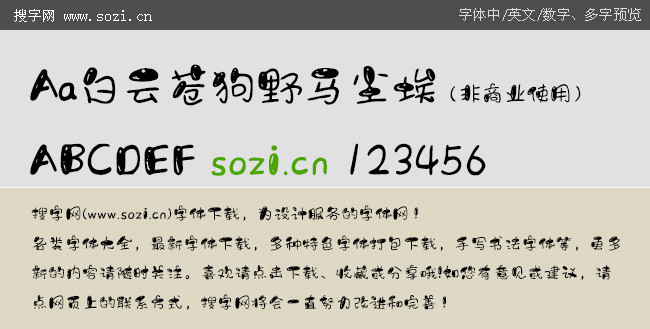
Aa白云蒼狗野馬塵埃
搜字網(wǎng)給大家提供一款A(yù)a白云蒼狗野馬塵埃(非商業(yè)使用)中文字體下載,該字體是一款卡通藝術(shù)字體,字體結(jié)構(gòu)巧妙活潑,字體的點(diǎn)筆畫多數(shù)呈圓點(diǎn)狀。適合書裝設(shè)計(jì)、包裝設(shè)計(jì)、海報(bào)設(shè)計(jì)等應(yīng)用(此字體為個(gè)人非商用版,商用可以聯(lián)系QQ:1006760504)。